日本字体广告设计为何能总给人一种清新淡雅的觉得?
现在是炎夏的季节,设计方案也可以给人产生清爽的觉得,日本国的清新自然排版设计和设计方案便是这类设计风格的典型性。日本国广告设计到底为何能够给人产生清爽别具一格的觉得呢?由于日本设计注重艺术创意,注重精美,注重关键点。总体又无失活跃性,细腻又无失设计风格。
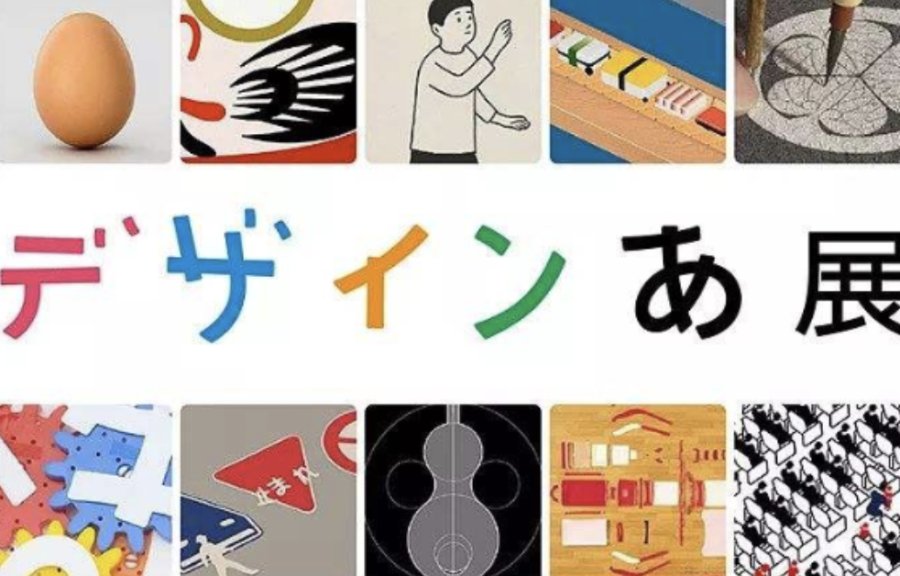
历数日本国广告设计的特性无非反映在下面的好多个层面:
一、精雕细琢
在广告设计上,日本设计和很注重排版设计,文本和图型的设计方案十分细致,排序也遵照着艺术美学和视觉效果规律性,基本上沒有随便的组成和排序。每一个关键点都绝不放过,这就是是日本设计和生活的态度。
二、艺术创意胆大
一些艺术创意的思绪和运用也是不可或缺的,无论让你的觉得荒不荒谬,日式风格设计方案追求完美的便是出乎意料的实际效果。这种雅趣通常能令人感觉眼前一亮。
三、线框排序
日本浮世绘针对西方国家文艺界和中国设计师都造成过关键的危害,注重排序,风格细致也是它的特性之一,去日本广告设计中也经常可以看到线框的排序和运用。
四、非对称
除此之外,日本设计的非对称构图法也是特别注意的特性,在广告设计的行业中,清楚便捷,简易平面构图、无装饰线条字体样式、横纵平行线构造全是广告设计行业常见的技巧。不管从传递清楚便捷的作用视角還是从界面的形象性看,应用非对称标准给设计方案产生全新升级的感观。
中西方文化艺术相融下的日本国的设计色彩是将艺术美和西方国家美融合在一起的。在颜色上很多采用光泽度、邻近色。
图案设计的组成和艺术创意也具备特点,即便维持了中华民族古典风格的艺术风格,但仍具备艺术创意的定义艺术美,这也是日本国的设计方案在全球设计史上一贯维持优异的影响力和水平的缘故。
日本国广告设计大概而言是以20世纪50年代刚开始发展的,但短短的已过三十年便位居全球设计方案强国。如今日本国广告设计早已含有自身十分明显的设计风格标识,因此日本国广告设计出国留学备受学员的钟爱。